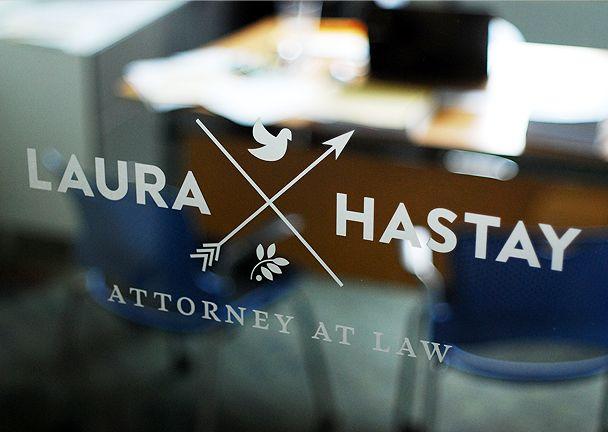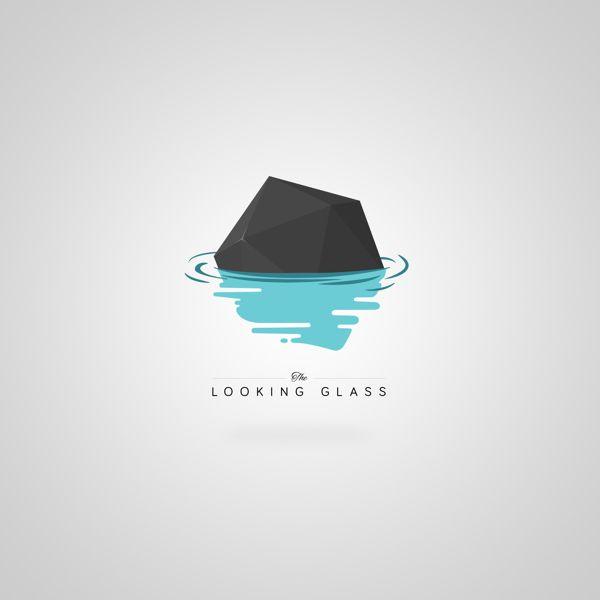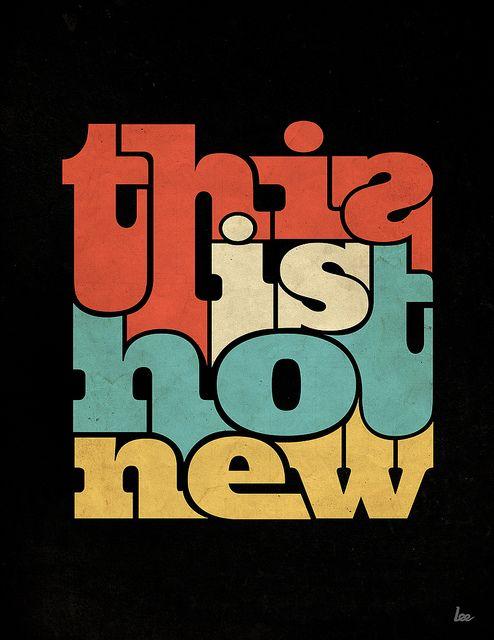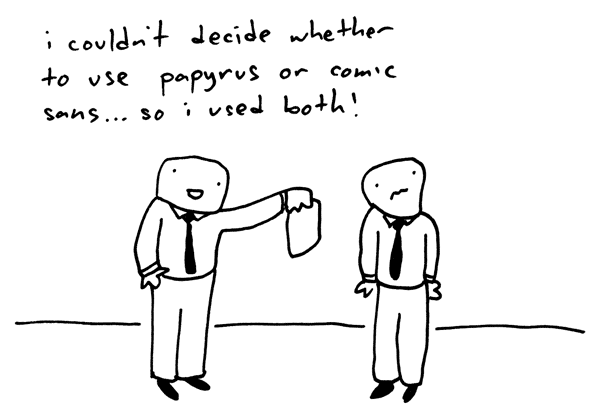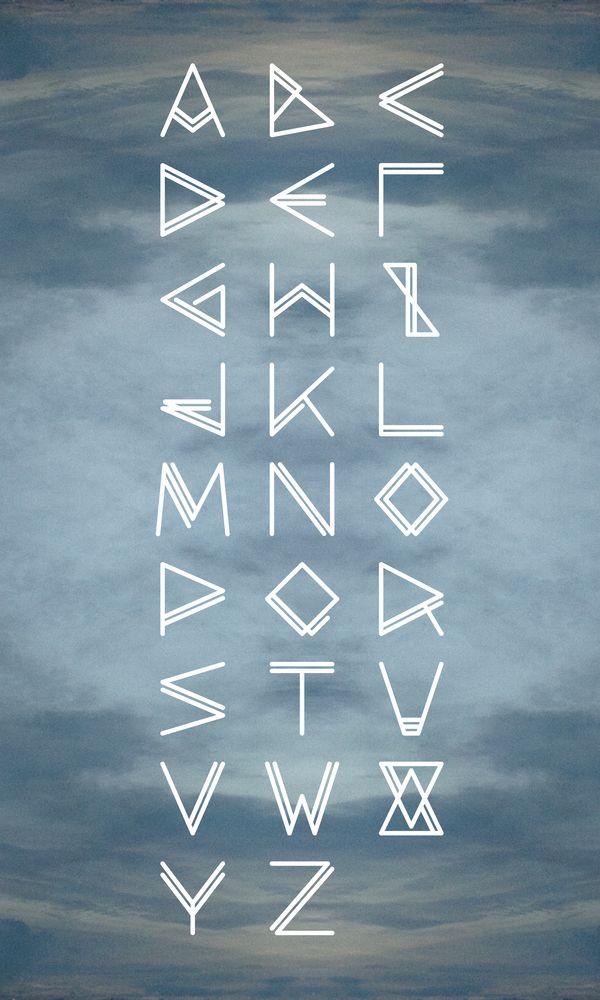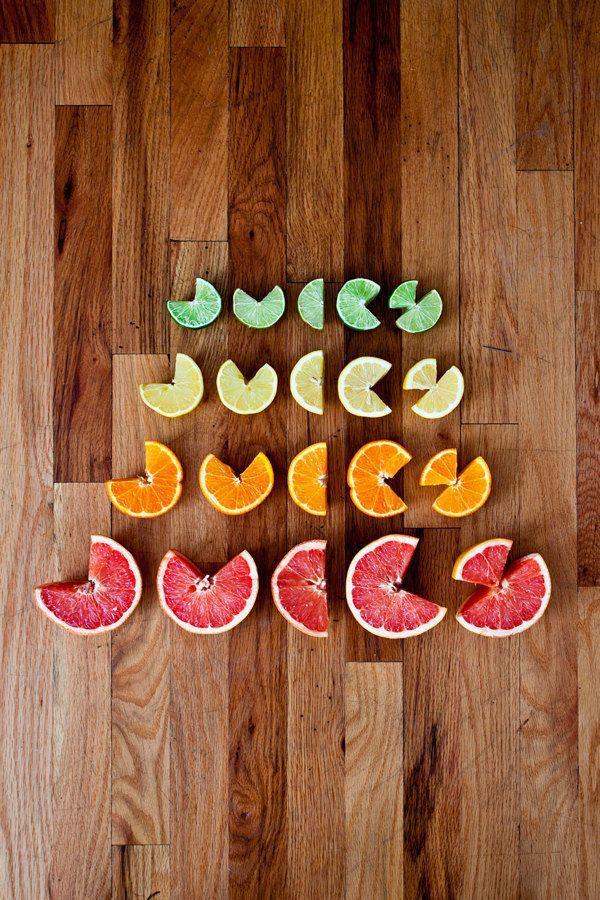
De tipos de letra va el asunto: ¿Cómo escoger una tipografía para nuestro logo?
Cada vez estamos más inmersas en el mundo de las marcas, crear una identidad que refleje quien eres es algo primordial, todo debe estar cuidado y medido. Y dentro de este mar de dudas que os suelen surgir  hay una que algunos ni se plantean pero a otros les quita más el sueño que los 40º a la sombra de la capital...
¿Qué tipografía uso?
Escoger una tipografía es un tema muy complicado. Sobre todo teniendo en cuenta, que una buena elección puede suponer aumentar la fuerza de tu marca y una mala, en cambio, dilapidarla. Entonces, ¿cómo escoger la tipografía de logo perfecta para tu marca entre todas las posibilidades que disponemos? ¡No preocuparse! Os vamos a dar unos cuantos consejitos para que no os volváis locos:
1.      TEN EN CUENTA EL PROPÓSITO
La elección del tipo de letra debe tener en cuenta el propósito de la comunicación. Por ejemplo, si tu empresa trata con asuntos legales o contables, lo propio es escoger un tipo de letra que transmita la idea de seriedad y potencie la confianza.
2.      SE ATEMPORAL
A todos nos gusta ponernos nostálgicos de vez en cuando, pero a la hora de escoger una tipografía hay que tener cuidado. Ten en cuenta que tu logo es la imagen directa de tu marca y su tipografía tiene que transmitir la esencia de la misma. No te unas a la moda del momento porque aunque parezca una solución rápida, seguramente te arrepentirás en menos de un año.
3.      DALE UN POCO DE ESPACIO
El trompetista de jazz Miles Davis una vez dijo que las notas que no tocas son tan importantes como las que sí. Así que ten en cuenta el espacio entre caracteres. Mucho espacio entre ellos genera aire y desunión, en cambio, caracteres muy juntos dan sensación de agobio.
4.      EVITA RELACIONES DIRECTAS
No uses Papyrus sólo porque de alguna manera la esencia tiene un rollito antiguo o está relacionado con Egipto.  De hecho, te recomendamos que nunca uses la letra Papyrus.
No uses Comic Sans por el tema es cómico o de humor. En realidad, mejor que nunca uses la letra Comic Sans.
Y, por último, no uses Lithos porque tu marca sea un restaurante griego.
5.      EVITA LO CONVENCIONAL
Sí, nuestro maravilloso ordenador viene de fábrica con una buena cantidad de fuentes variadas. El problema es que en todos vienen las mismas y nosotros no queremos que nuestra marca sea una más del montón. Así que abre tu mente, evita lo común y bichea en páginas que te den la opción de previsualizar. De esta manera, podrás verificar cómo queda antes de comprarla o descargarla. Para coger ideas os dejamos una página en la que podéis ver fuentes hechas por diseñadores para diferentes marcas. http://fontsinuse.com
Como veis, son cosas que a cualquiera se le pueden ocurrir aunque  cuando estás inmerso en la búsqueda puedes olvidar pero ya están aquí las tres pesadas de turno para recordároslo hasta la saciedad.